懐かしくて新しい レトロスタイルデザイン
最新レトロデザインを紹介した「懐かしくて新しい レトロスタイルデザイン」がパイ インターナショナルから2019年2月12日に発売された
インスピレーションをかきたてる、最新レトロデザインが満載
レトロなデザインはいつの時代も根強いファンが多く、様々な分野でクリエイターのインスピレーションを刺激してきました。本書では、古き良き時代のグラフィックデザインや印刷・加工技術に影響を受け、現代のエッセンスを巧みに加えた、斬新な作品の数々を紹介します。
レトロデザインスタイルなフォント「ロマン風書体」シリーズ
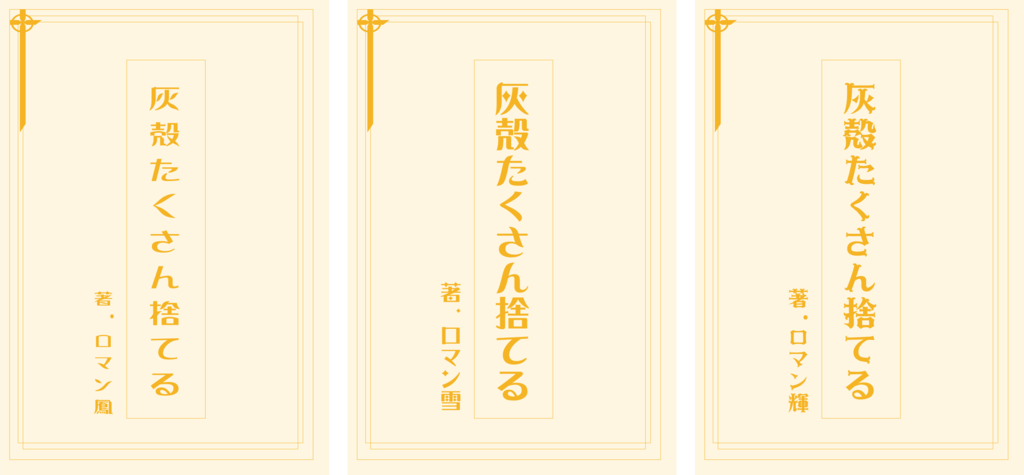
大正浪漫、昭和モダンなレトロスタイルなデザインに合うのがダイナフォントの書体「ロマン風書体」。ロマン雪、ロマン輝、ロマン鳳がある。